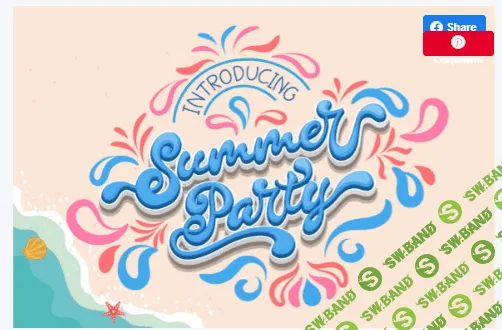
Название: Summer Party Font (2021)
Summer Party - причудливый, романтичный и шикарный рукописный шрифт. Этот шрифт имеет кодировку PUA, что означает, что вы можете легко получить доступ ко всем удивительным глифам и лигатурам! Влюбитесь в его невероятно универсальный стиль и используйте его для создания впечатляющих дизайнов!